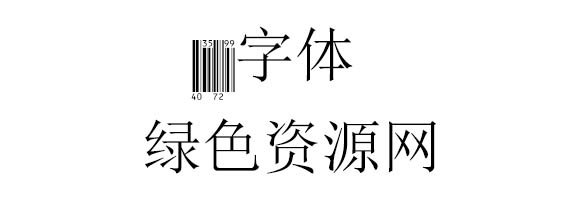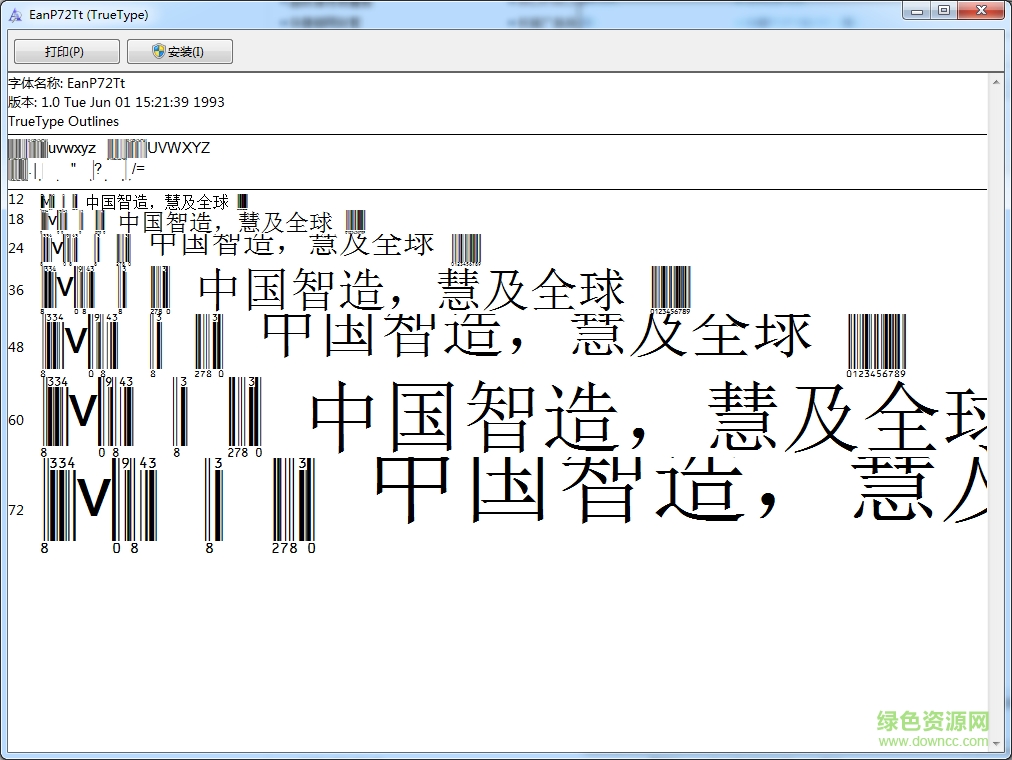
EanP72Tt字體是一款簡(jiǎn)潔大方的條形碼字體軟件,字體樣式簡(jiǎn)單大方,以條形碼方式來(lái)輸出字體和數(shù)字,使用便捷完全免費(fèi)??靵?lái)綠色資源網(wǎng)下載體驗(yàn)吧!
EanP72Tt字體是非常好看的條形碼字體,他會(huì)將數(shù)字字母等以條形碼的的形式帶個(gè)你,是不是很神奇了